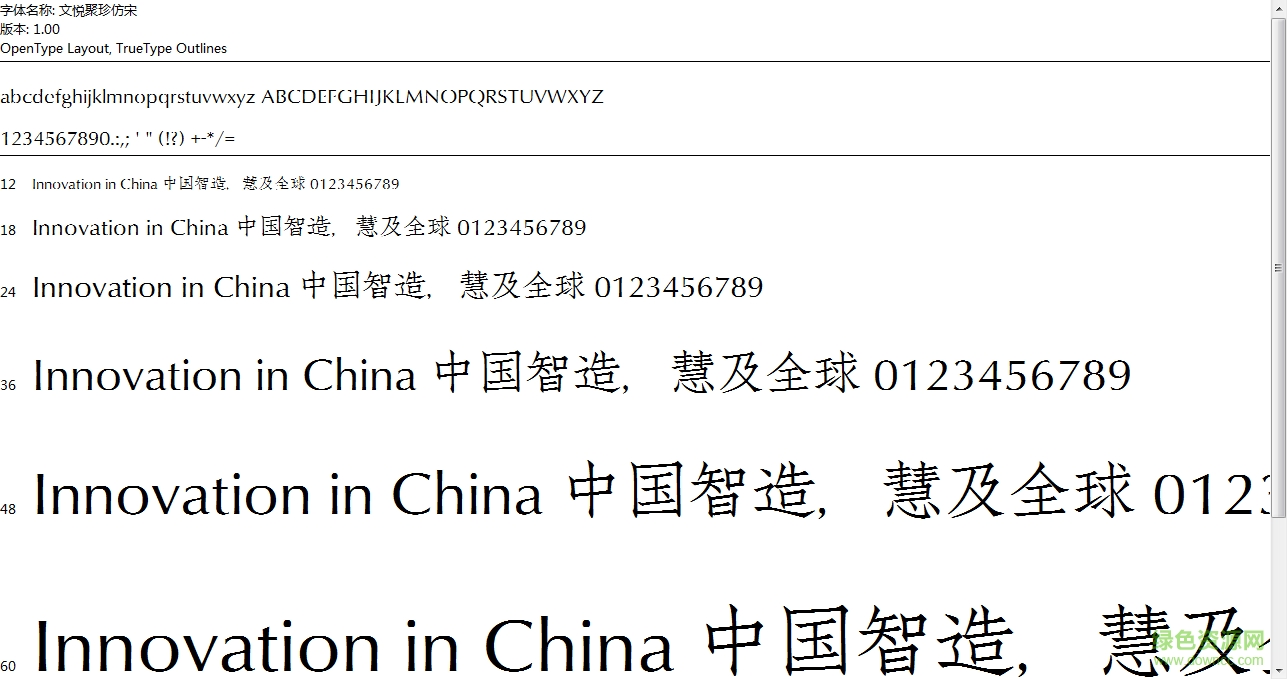
typeland juzhenfang字體即為文悅聚珍仿宋,是一款非常大氣的電腦字體,字體粗細(xì)均勻,使用起來如行云流水一般,廣大應(yīng)用于多種行業(yè)??靵砭G色資源網(wǎng)下載體驗(yàn)吧!
typeland juzhenfang是一款應(yīng)用于藝術(shù)設(shè)計(jì)方面的簡體中文字體,該字體筆畫粗壯,尾部的甩尾有力且有豐富的筆觸細(xì)節(jié),大字效果突出且引人注目;并且最大程度還原作者書寫字形,細(xì)節(jié)表現(xiàn)完整,且字庫完整,可以廣泛應(yīng)用于名片設(shè)計(jì)、新聞媒體、宣傳海報(bào)、ppt、影視制作以及內(nèi)容用字等領(lǐng)域。